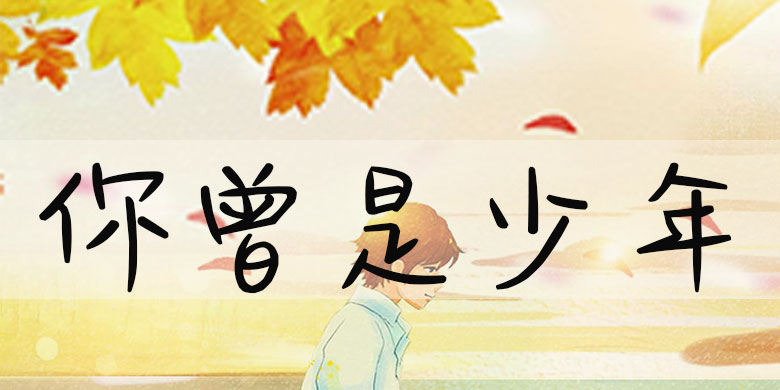
方正手迹-你曾是少年
字体品牌: 方正手迹 设计师:刘晔 字体分类:常规书写·硬笔 字体属性:精品字 字符集:大陆简体(GB2312-80) 发布时间: 2018
结构严谨,线条遒劲,柔中见刚,较少连笔,粗细变化有致,收笔较松,具有较强的现代气息,字里行间透出从容和优雅,让人赏心悦目,百看不厌。适用于文艺类的书刊、品牌广告和产品包装设计,以及社交网络的个性化用字。